松本タイポグラフィ研究会主催セミナー「書体と活字」シリーズ
松本タイポグラフィ研究会は平成30年開催予定のセミナー「書体と活字」シリーズの第一弾として「文字の食卓」を主宰する文筆家・正木香子氏を講師に「おいしい文字のチカラ」を開催する。「おいしい文字のチカラ」は2018年3月17日(土)に松本商工会館6階601会議室にて開催となる。この「書物と活字」シリーズの2018年のセミナー全3回を予定しており、第2回には鳥海修氏を招いて2018年7月28日(土)「本文書体の作り方と見方〈仮〉」が開催される予定。
主催となる松本タイポグラフィ研究会の白木隆士さんは「情報発信を担う書き手、デザイナーなどの作り手、そして読み手の三者がノウハウを共有、継承していくことで、より良質な活字文化が発信できる」と話している。
松本タイポグラフィ研究会は2017年冬に設立。メンバーは文字や書体、タイポグラフィに興味がある人や関連する仕事をしている人が中心で、仕事を終えた平日夜や休日に活動を行っている。「都市圏ではセミナーや勉強会も多いが、地方では学ぶ機会が少ない。知識や技術の習得が遅れることは、地方の仕事が都市圏に流出することにもつながっている」と白木さん。「松本は、こういう学びの場を受け入れる気風があると感じている。いずれは地方都市独特の文化を反映させた『松本書体』の開発をして、地域経済に貢献できれば」と意気込む。
第1回では、文字や組み版・デザインに興味を持つきっかけとなることを目指している。「デザイナーや文章の編集・組み版に携わる人はもちろん、本好きや文字が好きという人、極端に言えばそういうものに興味がない人でも面白い話が聞けると思う。気軽に参加してもらえれば」と呼び掛ける。
第1回セミナー「おいしい文字のチカラ」セミナー講師:正木香子氏
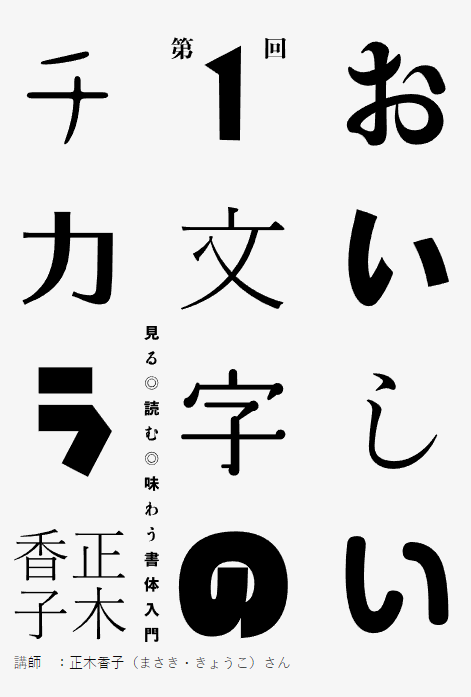
独自の書体批評で文字の面白さ、奥深さを伝えている文筆家、正木香子氏が講師を務める。マンガや文学に登場する様々な文字を通して滋味豊かな書体の世界を楽しみながら、戦後の活字文化を知り、日本語タイポグラフィを学ぶための基礎知識を身につけられる。文字の味わい方がわかれば、何気なく目にしていた文字の印象が、ガラリと変わるはず。
第2回「本文書体の作り方と見方〈仮〉」 セミナー講師:鳥海修氏
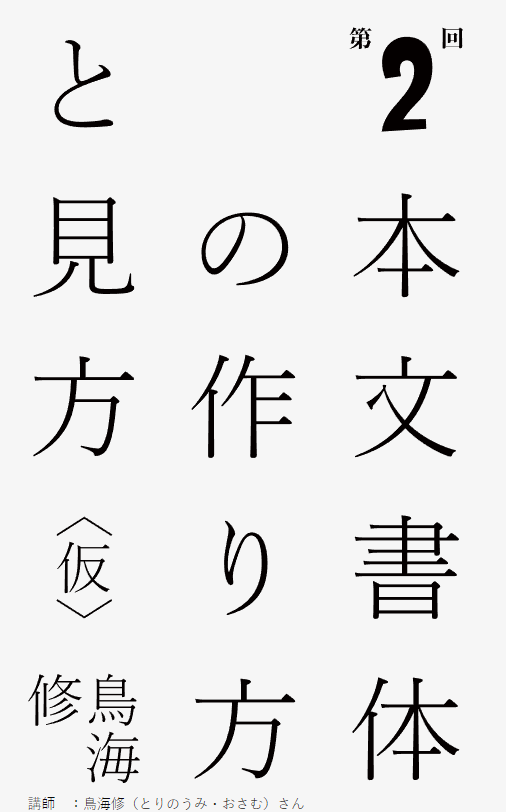
本や新聞、PCやモバイルなどで毎日、目にする文字。当たり前のように存在しているが、じつは読みやすさや美しさを追求するデザイナーの手によって生み出されている。
フォント制作会社「字游工房」の代表にして、書体設計士の著者は、どのように文字作りの道を目指し、歩んできたのか? これまでに制作した文字。その文字に込めた思想。理想の文字。影響を受けた人たちとの交流……。
「水のような、空気のような」書体を目指して活動してきた37年間を振り返り、これからの文字作りにつなぐ思いをつづる。
鳥海修Profile●1955年山形県生まれ。多摩美術大学卒業。書体設計士。79年株式会社写研入社。89年に有限会社字游工房を鈴木勉、片田啓一の3名で設立。現在、同社代表取締役。大日本スクリーン製造株式会社のヒラギノシリーズ、こぶりなゴシックなどを委託制作。一方で自社ブランドとして游書体ライブラリーの游明朝体、游ゴシック体など、ベーシック書体を中心に100書体以上の書体開発に携わる。2002年に第一回佐藤敬之輔顕彰、ヒラギノシリーズで05年にグッドデザイン賞、08年に東京TDCタイプデザイン賞を受賞。京都精華大学特任教授。